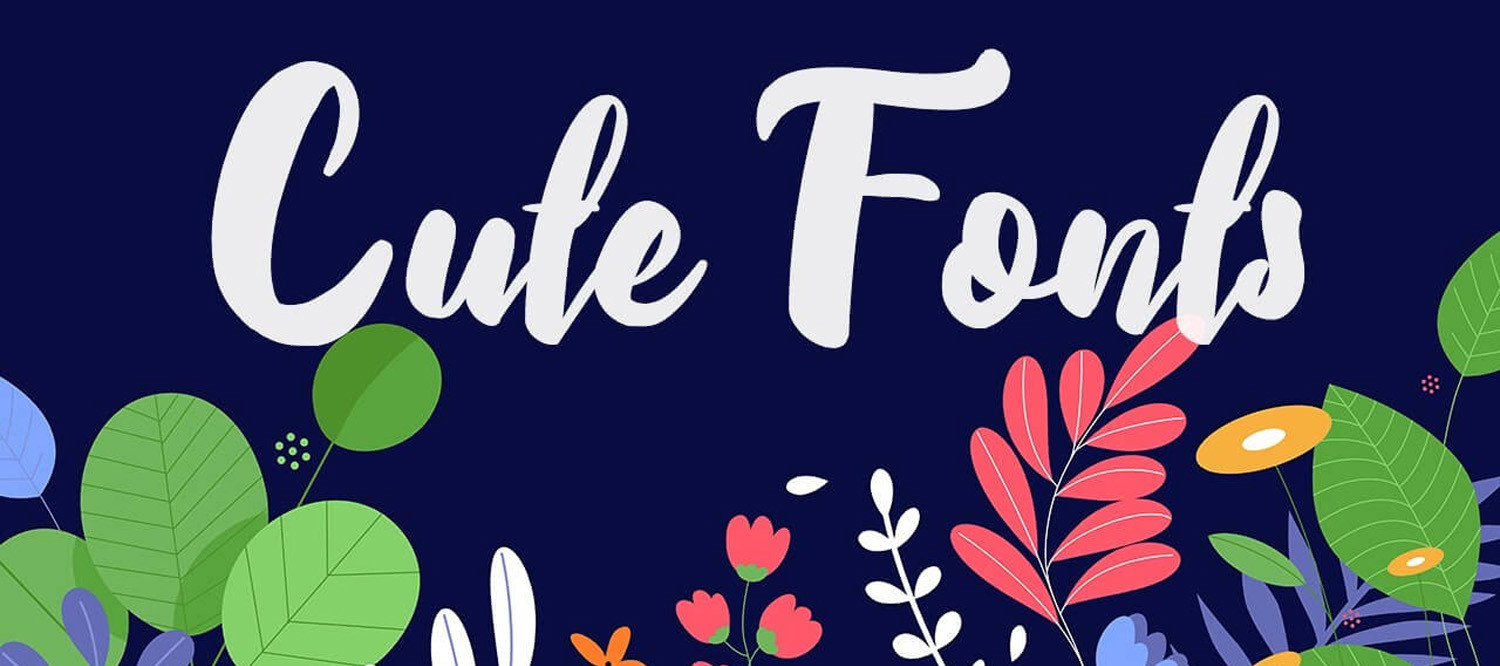
Font chữ không chỉ đơn thuần là những ký tự để truyền tải thông điệp mà còn là một yếu tố quan trọng trong thiết kế đồ họa và marketing nội dung. Trong thế giới kỹ thuật số ngày nay, có rất nhiều phong cách font chữ khác nhau để lựa chọn, từ trang nhã đến hiện đại, từ nghiêm túc đến dễ thương. Trong bài viết này, chúng ta sẽ khám phá sâu hơn về font chữ dễ thương, vai trò của chúng trong thiết kế, và cách sử dụng chúng để thu hút sự chú ý của đối tượng mục tiêu.
Font chữ dễ thương là những kiểu chữ có hình dáng đáng yêu, ngọt ngào, thường có các đường nét mềm mại, đơn giản và thường đi kèm với các chi tiết trang trí như hình vẽ hoặc các ký tự đặc biệt như hình trái tim, sao, ngôi sao,... Các font này thường được sử dụng để tạo cảm giác thân thiện, gần gũi và mang tính thẩm mỹ cao. Vai trò của font chữ dễ thương trong thiết kế đồ họa cụ thể như sau:
Tăng tính nhận diện thương hiệu: Việc sử dụng font dễ thương này có thể giúp thương hiệu của bạn nổi bật và dễ nhớ hơn trong lòng khách hàng. Những font này thường làm cho thương hiệu trở nên thân thiện và gần gũi hơn.
Thích hợp cho lĩnh vực dịch vụ và sản phẩm dễ thương: Nếu bạn làm việc trong lĩnh vực dịch vụ hoặc sản phẩm dành cho trẻ em, font chữ dễ thương sẽ rất phù hợp để tạo sự thân thiện và thu hút sự chú ý của đối tượng mục tiêu.
Tạo điểm nhấn trong thiết kế: Khi sử dụng font dễ thương trong thiết kế đồ họa, bạn có thể tạo ra điểm nhấn độc đáo và giúp thông điệp của bạn nổi bật hơn trong làn sóng thông tin hiện nay.
Các font chữ dễ thương được sử dụng phổ biến hiện nay thường có thiết kế đơn giản, trẻ trung và dùng trong các thiết kế đồ họa, trang trí, hay các sản phẩm dành cho trẻ em. Dưới đây là một số font chữ phổ biến để bạn có thể tham khảo:
Font chữ dễ thương Việt hóa HLT Sneaker Script được thiết kế để giống như viết tay tự nhiên, có sự cảm giác thân thiện và cá nhân. Nét chữ của font rất sôi động và trẻ trung, phù hợp cho các thiết kế đòi hỏi sự năng động và cá tính. Font có sự đa dạng trong các kết nối giữa các chữ cái, tạo nên sự mềm mại và trơn tru. Nhờ vào phong cách hiện đại, HLT Sneaker Script thường được sử dụng trong các thiết kế quảng cáo, bìa sách, poster, và các dự án sáng tạo khác.
Font chữ TH Mighty Kingdom là một lựa chọn tuyệt vời cho các thiết kế mang tính chất vui vẻ, dễ thương và thu hút trẻ em. Các ký tự được thiết kế với các đường nét mềm mại, tròn trịa, tạo cảm giác thân thiện và ngộ nghĩnh. Font chữ này có thể được sử dụng trong nhiều loại thiết kế khác nhau như thiết kế hoạt hình, bìa sách, đồ họa quảng cáo cho đồ ăn và các sản phẩm liên quan đến trẻ em. Khi kết hợp với các màu sắc tươi sáng, TH Mighty Kingdom càng trở nên nổi bật và phù hợp với các thiết kế cần sự sống động và bắt mắt.
Font chữ SVN-Gumley phù hợp cho các thiết kế dành cho trẻ em, đồ họa vui nhộn, hoặc các dự án sáng tạo cần sự ngộ nghĩnh. Chữ cái trong SVN-Gumley thường có dạng tròn trịa, mềm mại, tạo cảm giác dễ chịu và đáng yêu. Các nét chữ thường được uốn cong một cách nhẹ nhàng, không có góc cạnh sắc nhọn. Font chữ này thường có độ dày nét chữ vừa phải, không quá mỏng cũng không quá dày, đảm bảo sự dễ đọc và dễ nhìn.
SVN-Claytonia là một font chữ dễ thương và thanh lịch, được thiết kế để mang lại cảm giác mềm mại và thân thiện. Font chữ này thường được sử dụng trong các thiết kế dành cho trẻ em, thiệp mời và các sản phẩm đòi hỏi sự ấm áp và ngọt ngào.
Các ký tự trong SVN-Claytonia có đường nét mềm mại, uyển chuyển, tạo cảm giác dễ thương và dễ đọc. Font này mang phong cách viết tay, giúp tạo nên sự gần gũi và thân thiện trong thiết kế.
Font chữ TH Cupid Darling với các ký tự có vẻ ngoài giống như chữ viết tay, với các nét cong và mềm mại, tạo cảm giác gần gũi và thân thiện. Đặc trưng của font này là các nét chữ nhẹ nhàng, không quá nghiêm túc mà hướng đến sự đáng yêu và tinh nghịch.
Font chữ này thường được sử dụng trong các thiết kế liên quan đến chủ đề dễ thương như thiệp mời, trang trí, đồ họa cho trẻ em, và các sản phẩm có yếu tố thời trang, làm đẹp. Font thường có tông màu pastel hoặc những gam màu nhẹ nhàng, tạo nên sự hài hòa với các thiết kế dễ thương.
Font SVN-Kitten là một font chữ được thiết kế đặc biệt để có vẻ ngoài đáng yêu và thân thiện. Đây là một trong những font chữ Việt hoá được ưa chuộng, đặc biệt là trong cộng đồng yêu thích thiết kế và đồ họa. Font đã được Việt hoá một cách chuẩn xác, hỗ trợ đầy đủ bảng mã tiếng Việt, bao gồm cả các dấu thanh và dấu câu đặc biệt. Dù không quá phức tạp, SVN-Kitten vẫn mang đến sự cá nhân hóa và độc đáo cho bất kỳ thiết kế nào sử dụng nó.
Font chữ SVN-ARCO với những đường nét mềm mại và các chi tiết trang trí nhẹ nhàng. Thiết kế của nó phù hợp với các dự án sáng tạo, quảng cáo, hoặc bất kỳ ứng dụng nào cần mang lại cảm giác thân thiện và gần gũi. Những đặc điểm này làm cho SVN-ARCO trở thành lựa chọn tuyệt vời cho các thiết kế liên quan đến trẻ em, sự kiện vui nhộn, hoặc các sản phẩm có tính giải trí cao. Bạn có thể sử dụng font này để tạo ra các tiêu đề bắt mắt, logo hoặc các bài viết đồ họa cần sự nhí nhảnh và đáng yêu.
Font chữ dễ thương không chỉ đơn giản là một công cụ thiết kế mà còn là một phần quan trọng trong việc xây dựng và phát triển thương hiệu. Việc lựa chọn và sử dụng chúng một cách khéo léo sẽ giúp bạn tạo ra các thiết kế độc đáo và thu hút sự quan tâm của khách hàng mục tiêu. Hãy cân nhắc sử dụng font chữ dễ thương trong chiến lược thiết kế của bạn để tạo nên những trải nghiệm thú vị và đáng nhớ cho người dùng.